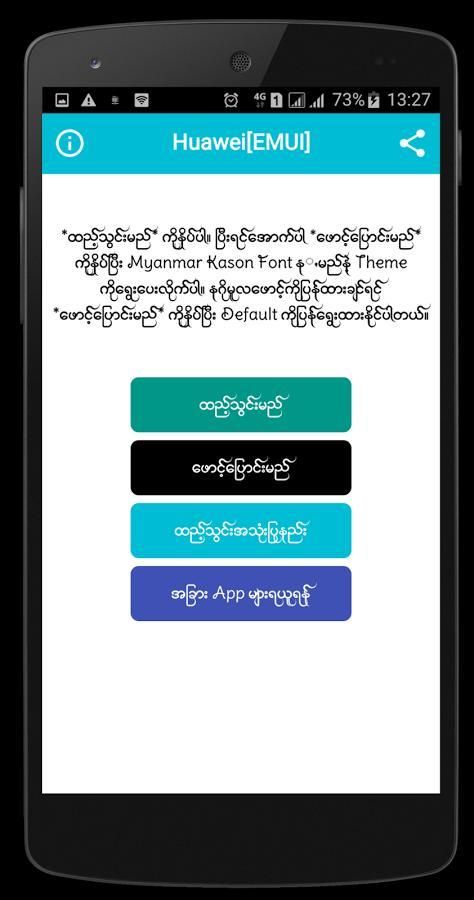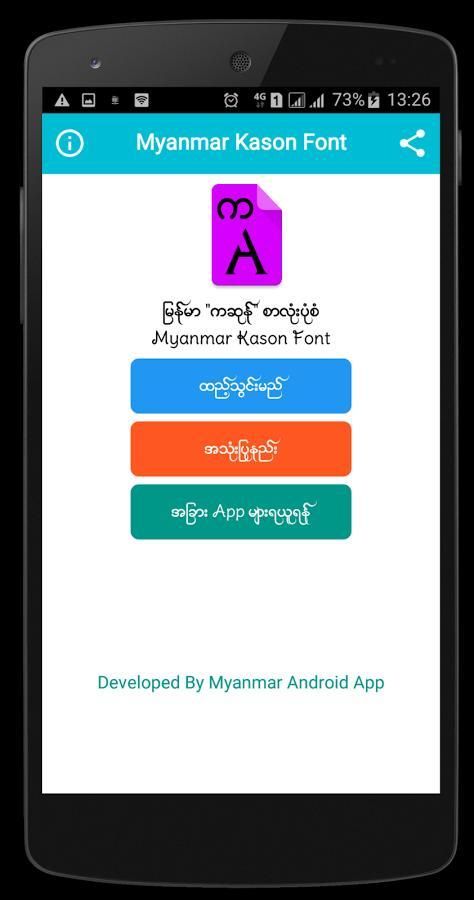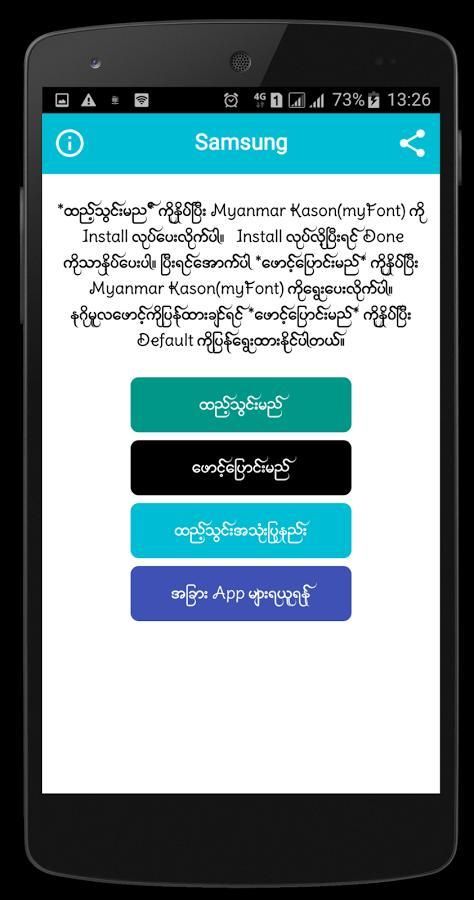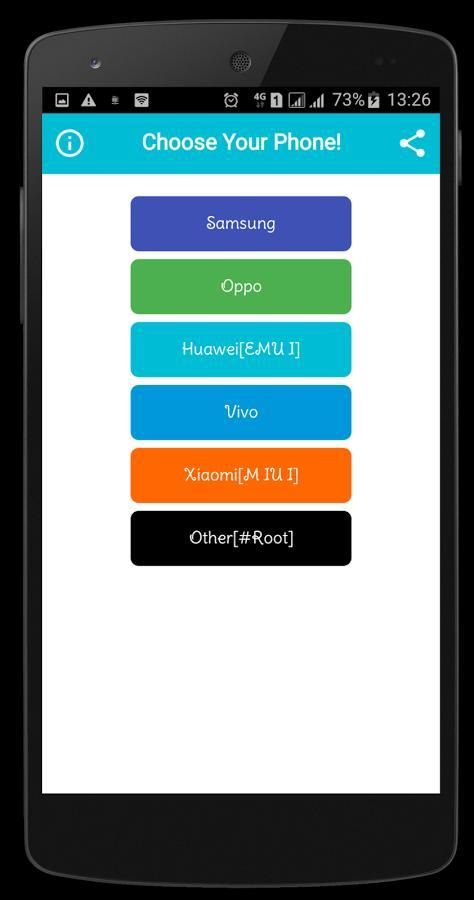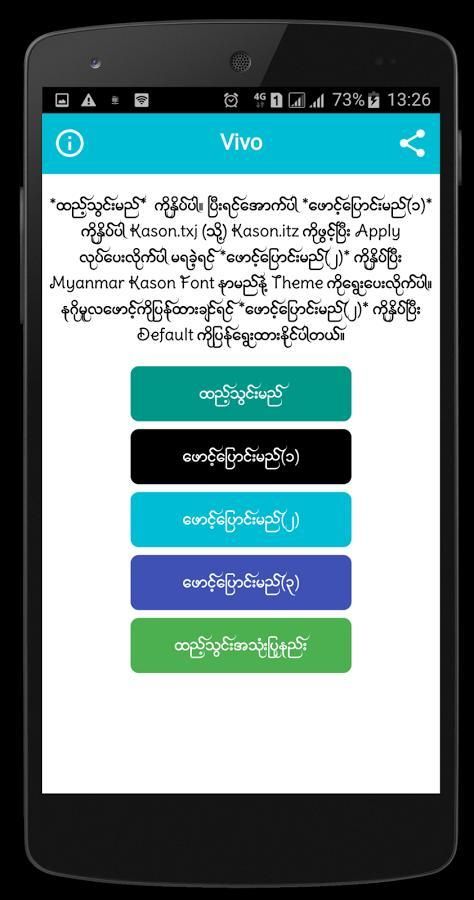
Myanmar Kason Font
"Myanmar Kason Font" Root မလိုထည့္သြင္း ျမန္မာစာလုံးအလွတစ္ခုျဖစ္ပါသည္။
ဖုန္းမွာျမန္မာစာလုံးအလွသုံးခ်င္သူမ်ားအတြက္
Myanmar Kason ဆိုတဲ့စာလုံးအလန္းေလးတစ္ခုပါ။
အရမ္းလန္းပါတဲ့စာလုံးပုံစံေလးပါ။
"Myanmar Kason" Font is Beautiful Myanmar Zawgyi Font Style!